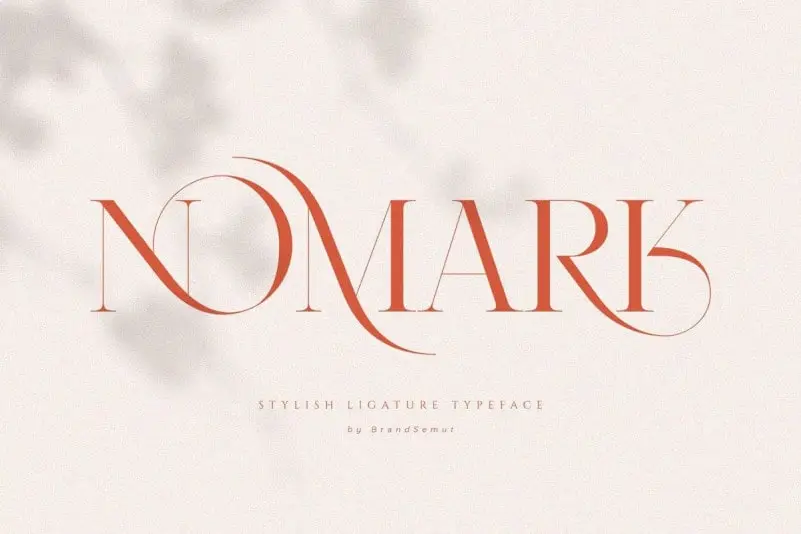
A Nomark Serif Font é uma elegante tipografia serif que se destaca no universo das fuentes modernas e nostálgicas. Criada para projetos profissionais de marca, esta fonte combina sofisticação com um toque moderno, adequado tanto para logotipos quanto para qualquer projeto gráfico. A designer BrandSemut trouxe sua habilidade artística para criar uma opção ideal para aqueles que buscam elegância e classe em suas criações digitais. Para designers buscando trazer aos seus projetos um toque de elegância, estilo moderno e sofisticação, a Nomark Serif Font é perfeitamente adaptada. Esta fonte já está pronta para ser usada juntamente com outros elementos, garantindo uma integração perfeita em qualquer projeto. Ideal tanto para personalizar as suas criações quanto para criar uma identidade visual consistente, esta fórmula de sucesso de design vem revolucionar a maneira como você visualiza e trabalha com seu trabalho artístico.